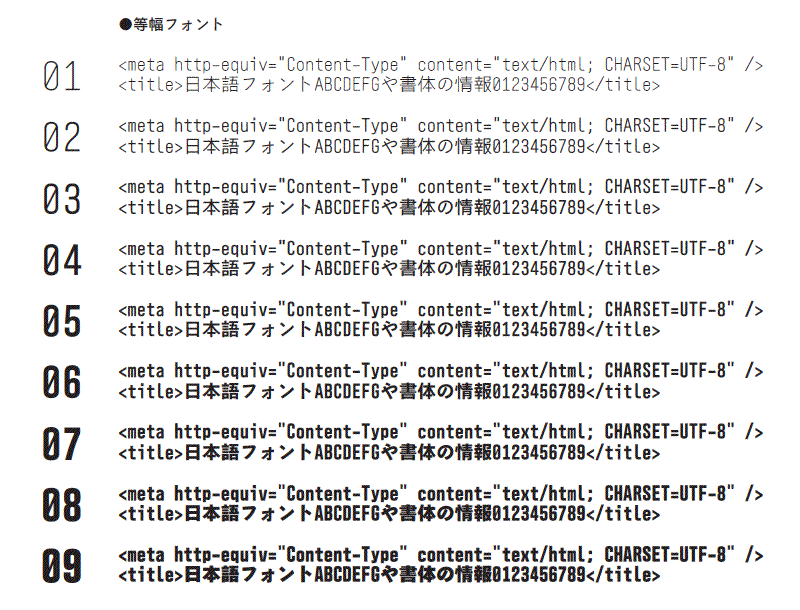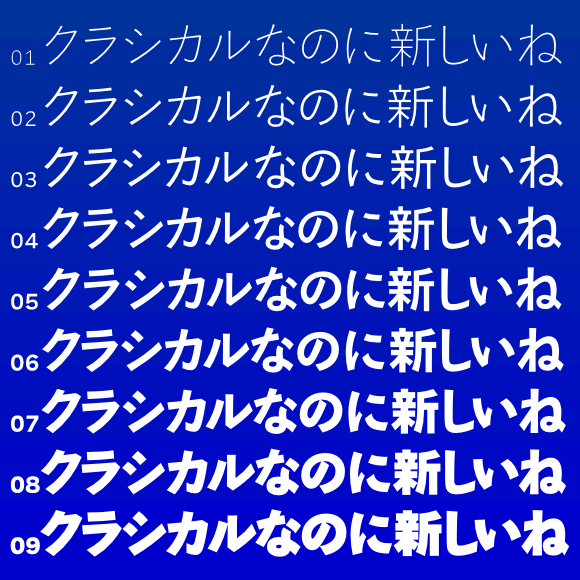
墨東ルイカ清音教漢-01〜09(無料お試し版)
墨東ルイカ-01〜09(商品版)
| デザイン |
古典的なカタチの「かな文字」と、現代的な雰囲気の「漢字」が、読みやすく新鮮な文字組イメージを創り出します。 太さが9種類あるので、使用環境や目的に合った最適なフォントが選べます。 等幅バージョンは、英大文字のアイ「I」と英小文字のエル「l」数字のいち「1」や、英大文字のオー「O」と数字のゼロ「0」が、はっきり区別がされているので、URL表記やプログラム編集などにぴったりです。 |
連想されるイメージ 寄せられたコメントから抜粋 |
文字に力がある・バランスが良い・読みやすい・やさしい・柔らかい・上品・本格っぽい・姿勢が良い。 |